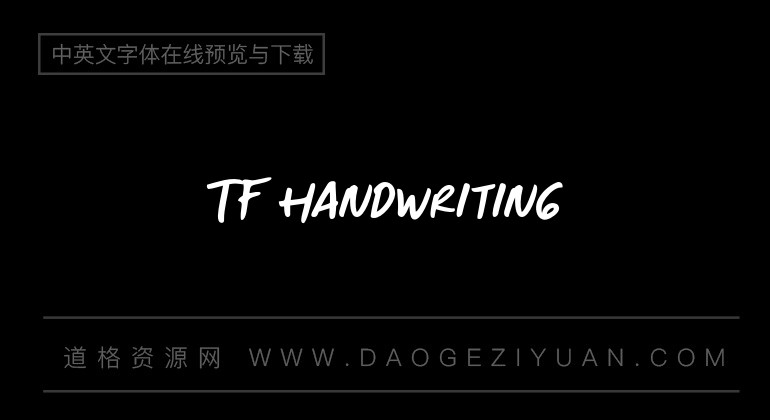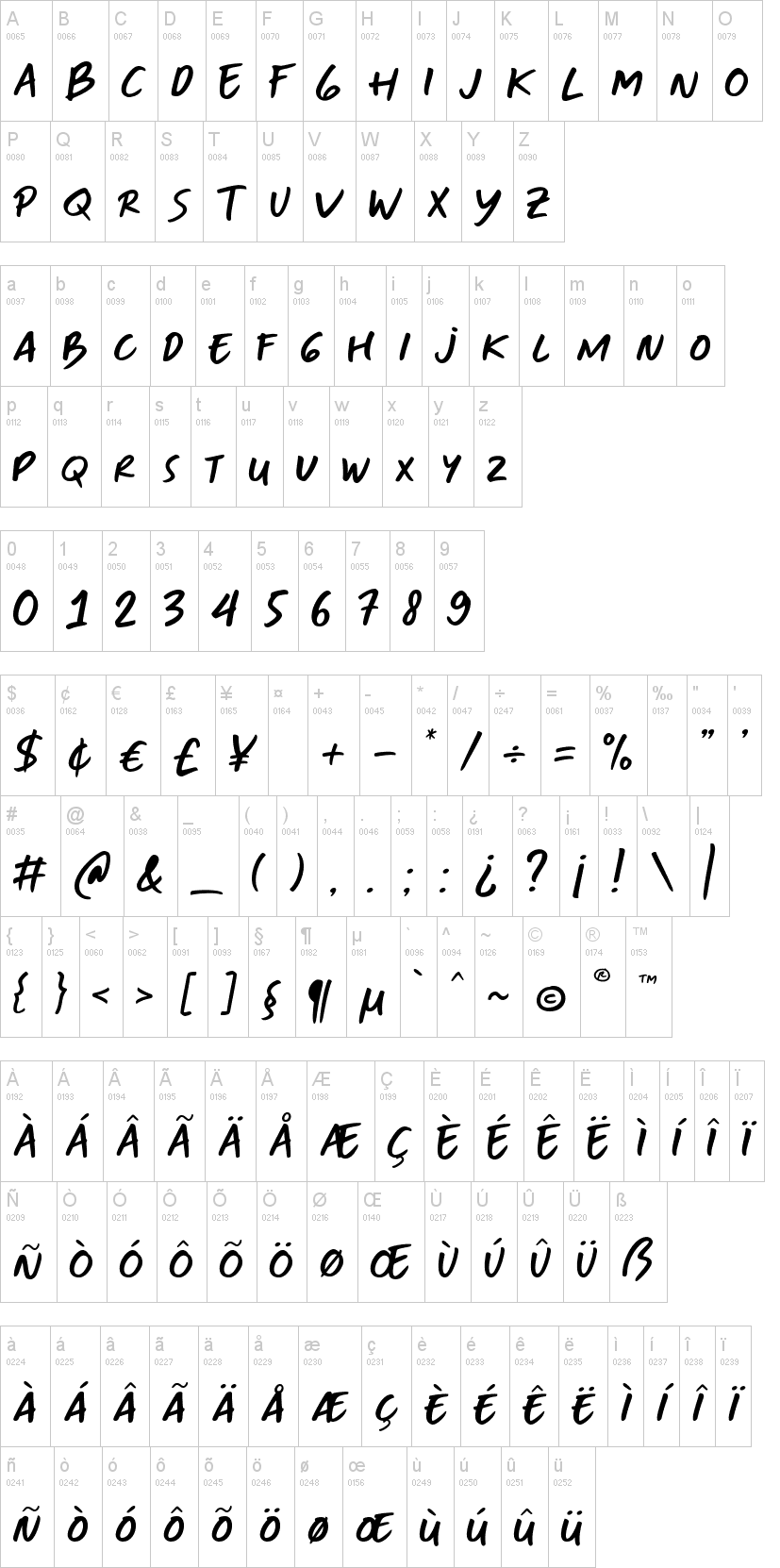
TF Handwriting 是一款由 TypeTogether 公司设计的手写字体,它的特点是有自然的笔画,具有良好的可读性,并且可以让您的文字看起来更加有趣。TF Handwriting 字体包含了大量的字符,可以支持多种语言,是一款非常灵活的字体,可以用于各种不同的设计项目中。它还支持多种字体格式,可以在多种平台上使用,比如 Windows,Mac,Linux,Android 和 iOS。内容介绍
TF Handwriting是一款非常不错的手写艺术字体,具有很好的视觉感,适合于文化类的宣传设计、商业类品牌的广告和产品包装设计以及个性化文字排版等较多场景。